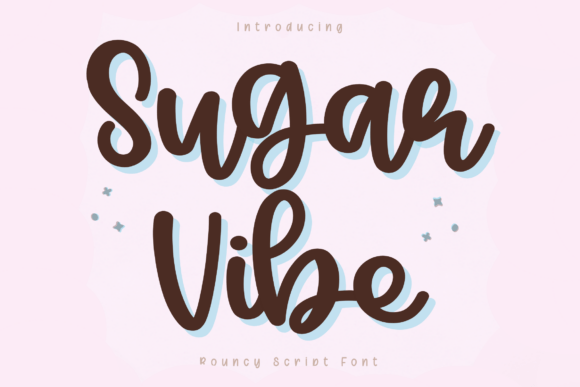
Sugar Vibe
Ulasan Lengkap Sugar Vibe: Font Script yang Menggugah Selera
Jika Anda sedang mencari jenis huruf yang memadukan kehangatan tangan-tangan terampil dengan kesan modern, Sugar Vibe adalah solusi sempurna. Font script ini tidak hanya cantik, tapi juga penuh dinamika yang membuat tulisan Anda terlihat begitu hidup—seperti tinta marker yang mengalir dengan bebas. Berikut ulasan mendalam mengenai Sugar Vibe dan alasan mengapa font ini cocok untuk brand Anda.
- Desain Berani dan Fluid – Huruf-hurufnya tebal, namun tetap lembut dengan terminal melengkung. Loop-loop tinggi menambah sentuhan “high‑energy” yang memikat.
- Hubungan Organik – Setiap karakter saling terhubung secara alami, menciptakan kesan satu alur yang rapih tapi tetap santai.
- Multifungsi – Ideal untuk branding bakery, merchandise lucu, kemasan snack artisanal, atau bahkan konten media sosial yang ingin menunjukkan keunikan.
- Prestise Artisanal – Meskipun ringan, Sugar Vibe menambahkan sentuhan profesionalitas, memberi tampilan “polished artisanal prestige” pada pesan visual Anda.
- Personalisasi Unik – Setiap huruf berbicara dengan karakter tersendiri, membuat merek Anda mudah dikenali dan berbicara langsung dengan audiens.
Dengan Sugar Vibe, pesan Anda tidak hanya dibaca, tapi juga dirasakan. Ciptakan identitas visual yang tak terlupakan, dan biarkan setiap huruf mengalir membawa kelezatan dan energi baru ke dalam brand Anda. Yuk, tambahkan Sugar Vibe ke proyek desain Anda dan rasakan perbedaan!